粗衬线字体
7. Breton
由设计师Daniel Hernández, Rodrigo Fuenzalida设计的Breton是一款受波士顿启发的几何粗衬线字体。共包含10种字重,并包括匹配的斜体。每种字体样式都包含417个字符,这些字符支持超过200种基于拉丁语的语言。
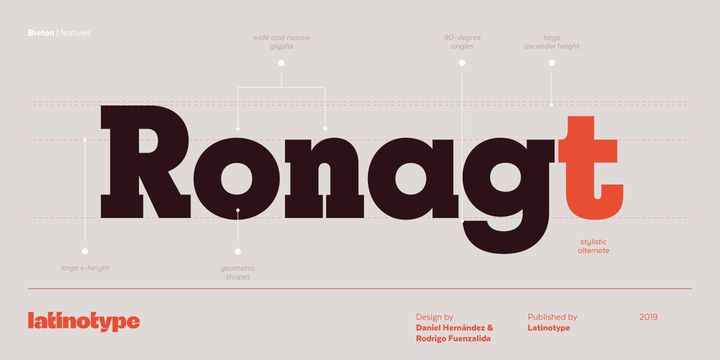
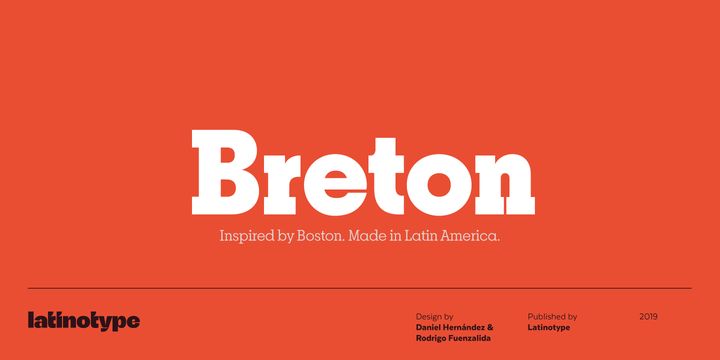
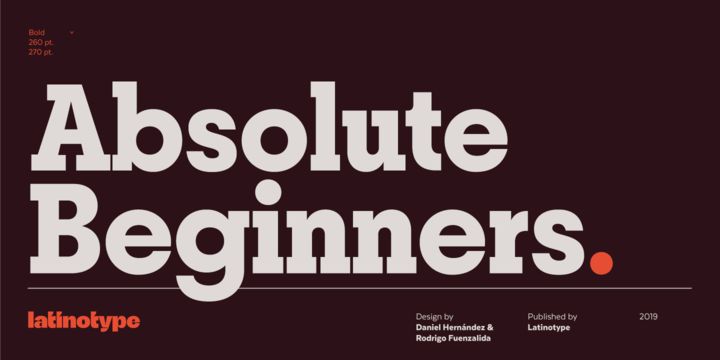
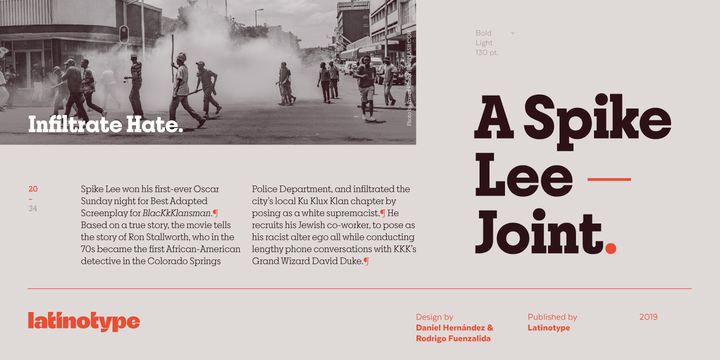
8. Klose Slab
由设计师Cahya Sofyan设计的Klose Slab,是今年9月发布的一款可爱的复古字体。附带4种样式(Condensed、Normal、Semi expanded、Expanded),也提供可变字体格式,同时支持75种以上的语言。
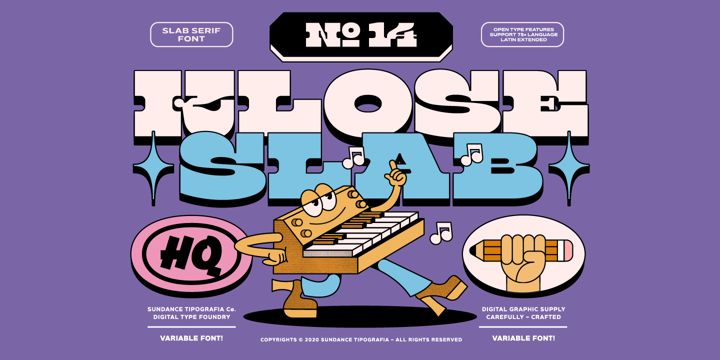
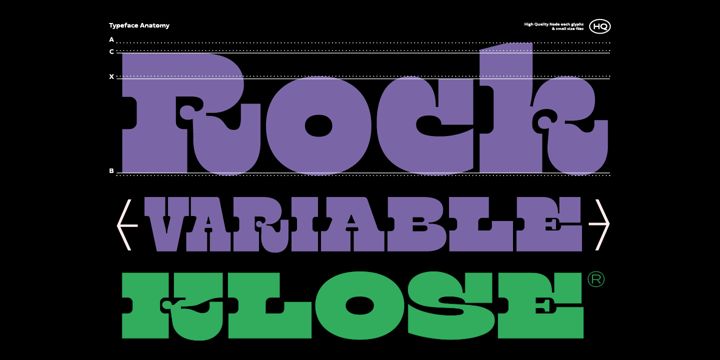
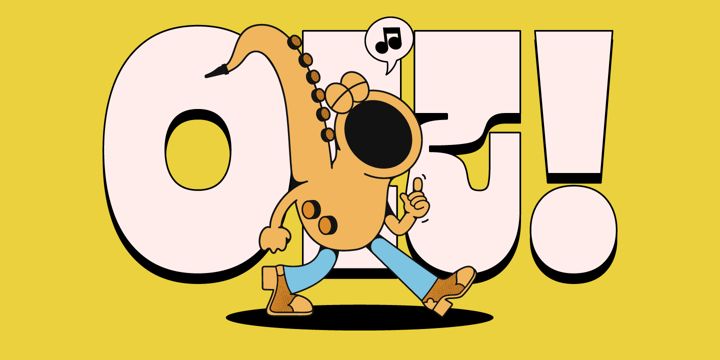
9. ITC Lubalin Graph
ITC Lubalin Graph最初是由Herb Lubalin在1974年作为前卫哥特式的演变而设计的,并代表了20世纪70年代美国平面设计的排版风格。
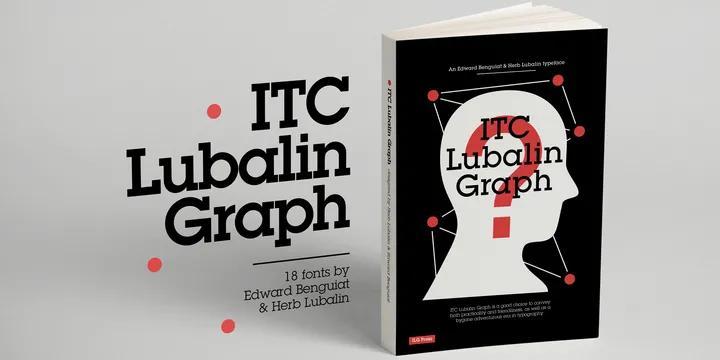
10. Sentinel
由设计师Jonathan Hoefler和Tobias Frere-Jones在2009年为Hoefler & Co公司设计。是一款涵盖多种字重的字体家族,同时具有清晰和富有表现力的字体。
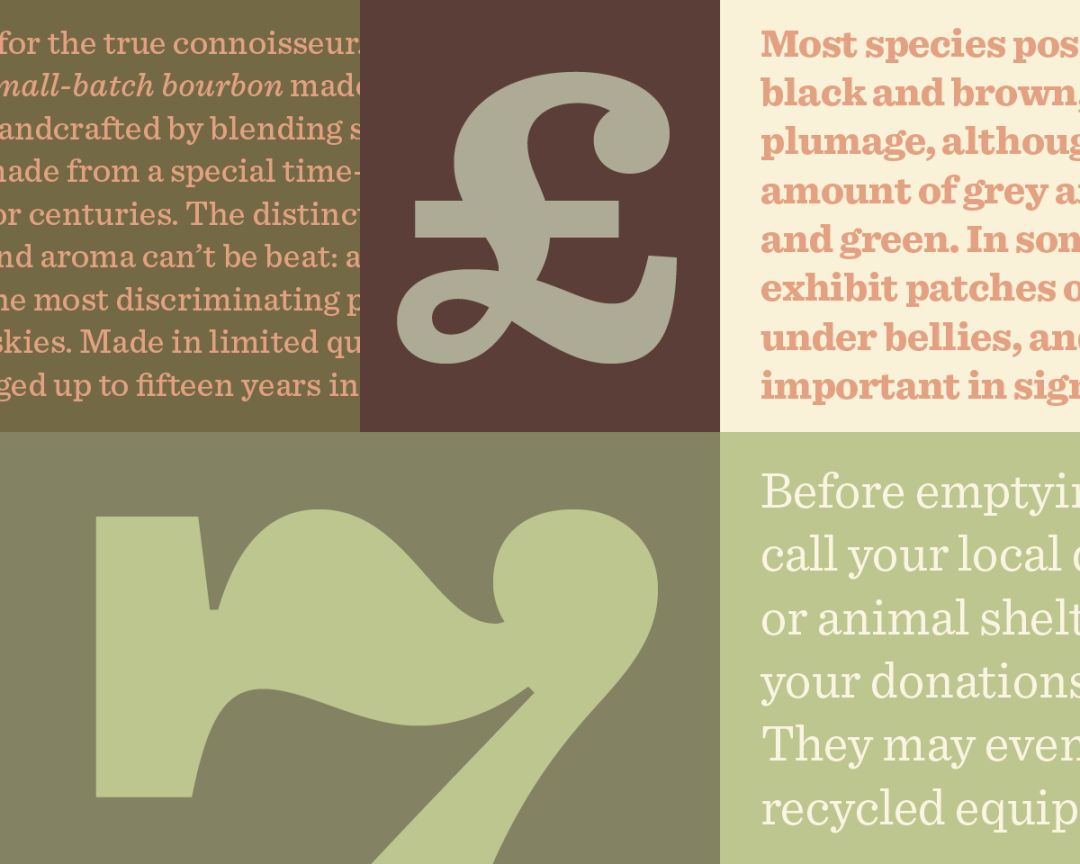
原标题:字体趋势:2021年将流行的24款字体